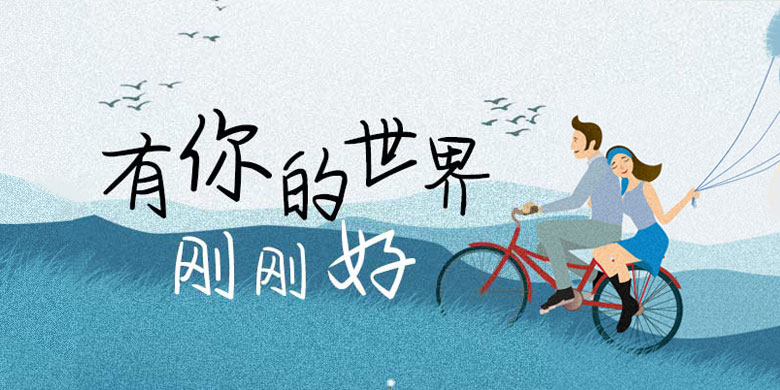
方正手迹-有你的世界刚刚好
字体品牌: 方正手迹 设计师:余丹 字体分类:创意书写 字体属性:精品字 字符集:大陆简体(GB2312-80) 发布时间: 2020
该字结构较为灵活,笔画粗细均匀。部件设计上别具一格,使得该字的性格更为丰满。适用于文艺类的书刊、品牌广告和产品包装设计,以及社交网络的个性化用字。